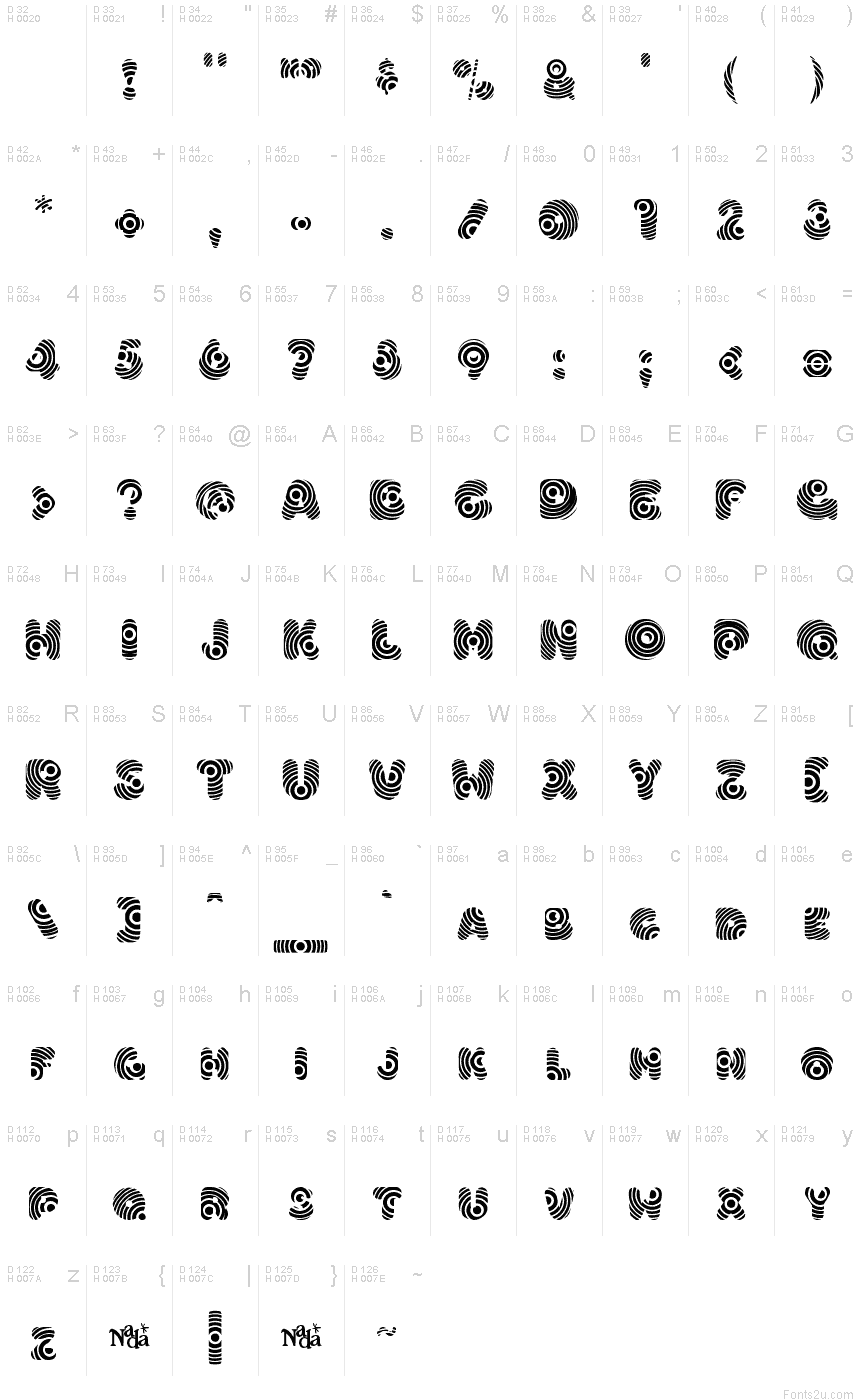
Hypmotizin od R. Gast to darmowy, groovowy krój displayowy, który wygląda, jakby został wyjęty prosto z kręcącej się płyty winylowej. Każda litera jest wyrzeźbiona z grubych, atramentowych pierścieni, które pulsują na zewnątrz, tworząc tripową teksturę op-art, która niemal porusza się na ekranie. Gęste czarne paski i wyrzeźbiona negatywowa przestrzeń nadają każdemu słowu silny wizualny rytm, już na pierwszy rzut oka.
Z Hypmotizin Twoje nagłówki nie leżą bezczynnie – pulsują jak światła w klubie. Ten darmowy font świetnie sprawdza się na ulotkach rave’owych, plakatach w stylu lat 70., logotypach DJ-skich, festiwalowym merchu, psychodelicznych zinach i odważnych grafikach do social mediów. Stosuj go w dużym rozmiarze i z dużymi odstępami, a w tekście głównym połącz z prostym bezszeryfowym krojem geometrycznym, aby hipnotyzujące kształty mogły w pełni wybrzmieć.